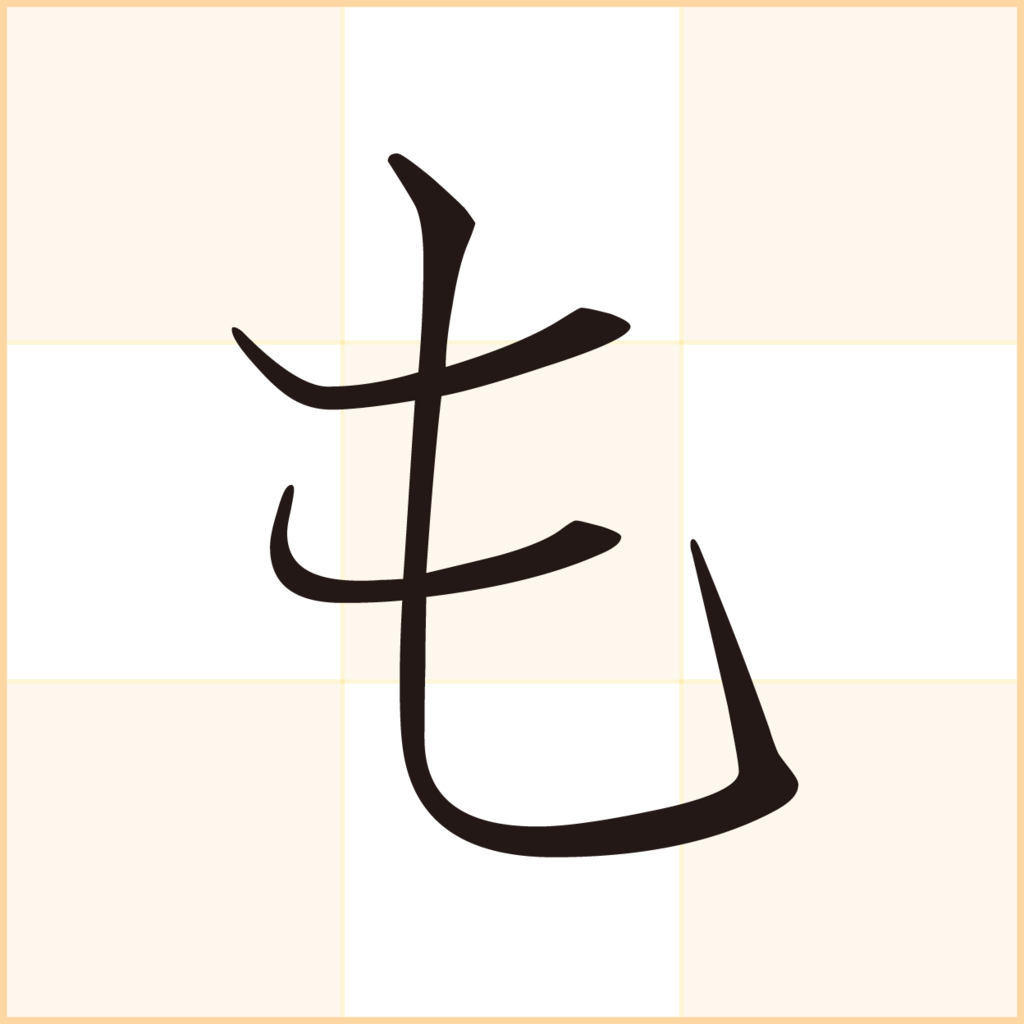
新宋体
中国の宋の時代に木版印刷に用いられた楷書の印刷書体である宋朝体を基にした書体。
新宋体の和文用仮名は「有限会社 字游工房」が制作している。
新宋体の組見本
新元号「令和」新宋体書体見本
新元号「令和」の新宋体の書体見本。
新宋体は化物語などの物語シリーズに使用
新宋体は化物語など、「物語」シリーズのタイトルとして使用されている。
ダイナフォントの2種類の宋朝体「新宋体」と「玉刻華宋」を比較してみた
ダイナフォントでは宋朝体としてメディアミックスなどされて人気を博した「物語シリーズ」などで使用されてきた新宋体に続き、2021年5月にデジタル向けの宋朝体である玉刻華宋をリリースした。
そこで新宋体と玉刻華宋を並べて比較してみた。
並べてみると、漢字とかなは新宋体のほうがより縦長でスマート、また、ストロークから鋭い印象を受ける。
逆に玉刻華宋はデジタル用にカスタマイズされているためだろうか、新宋体より柔らかく滑らかな印象を受けた。